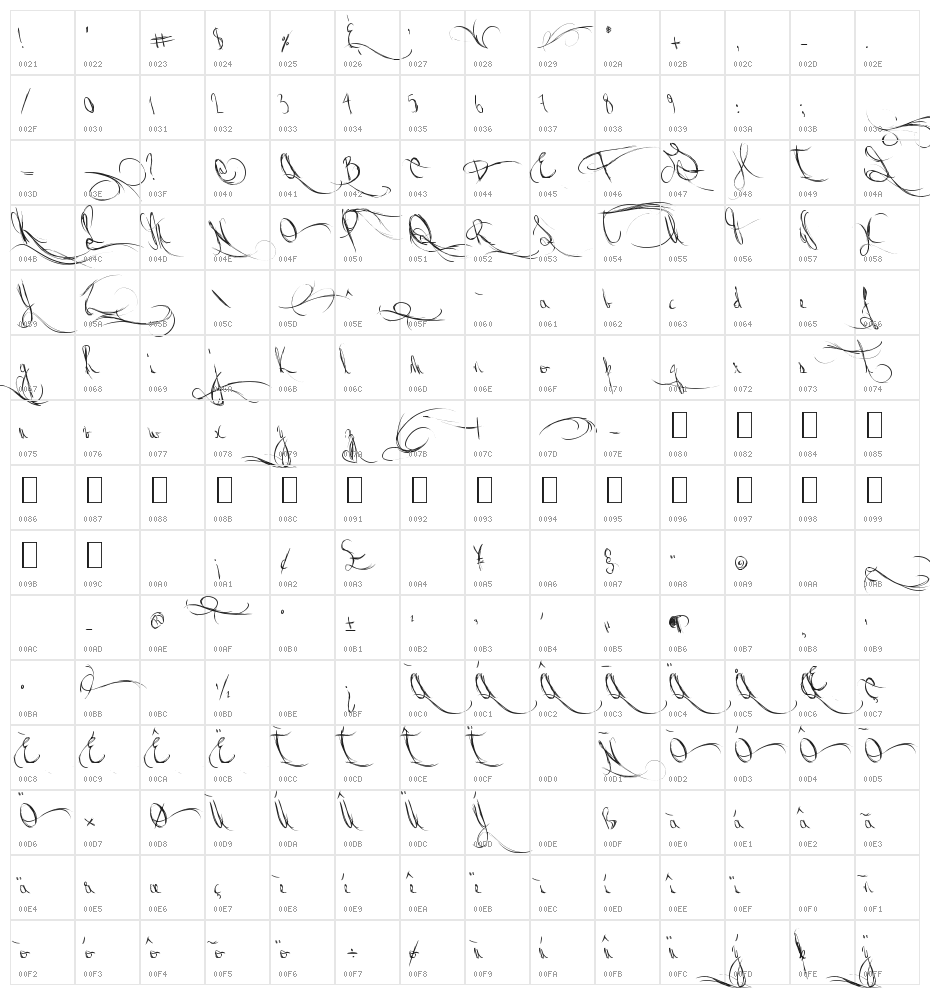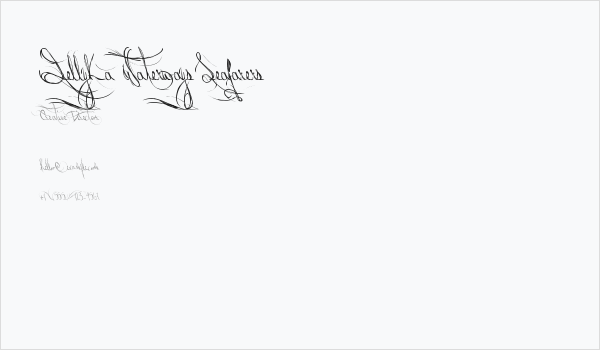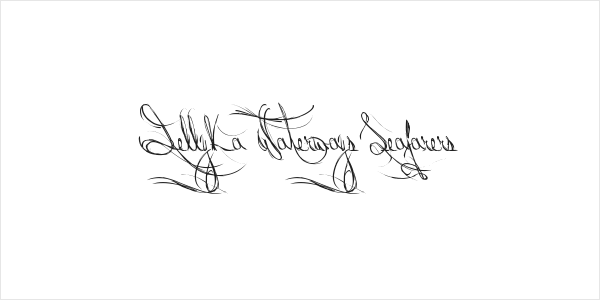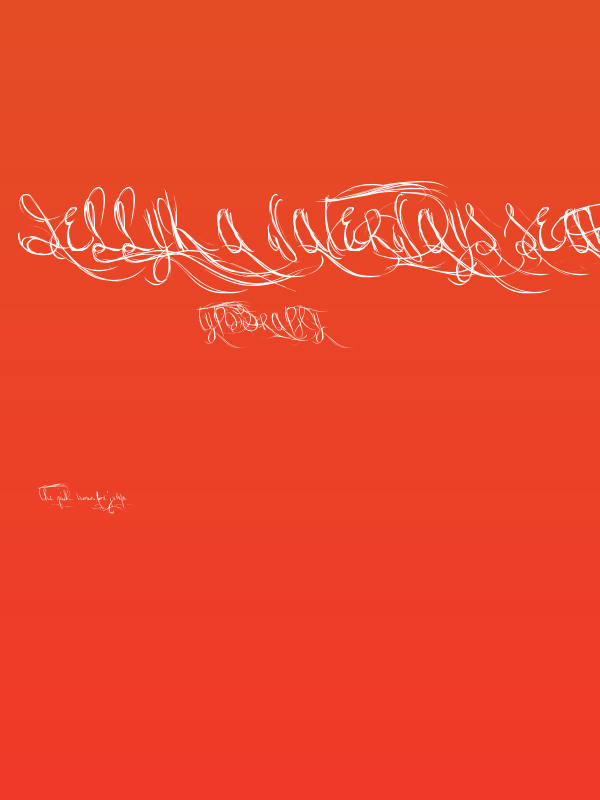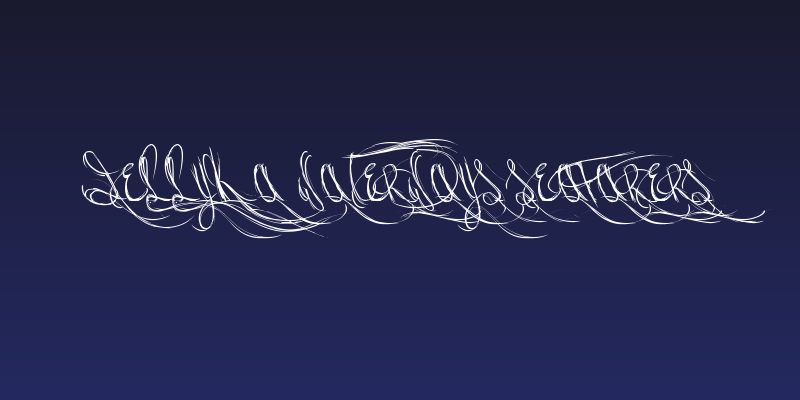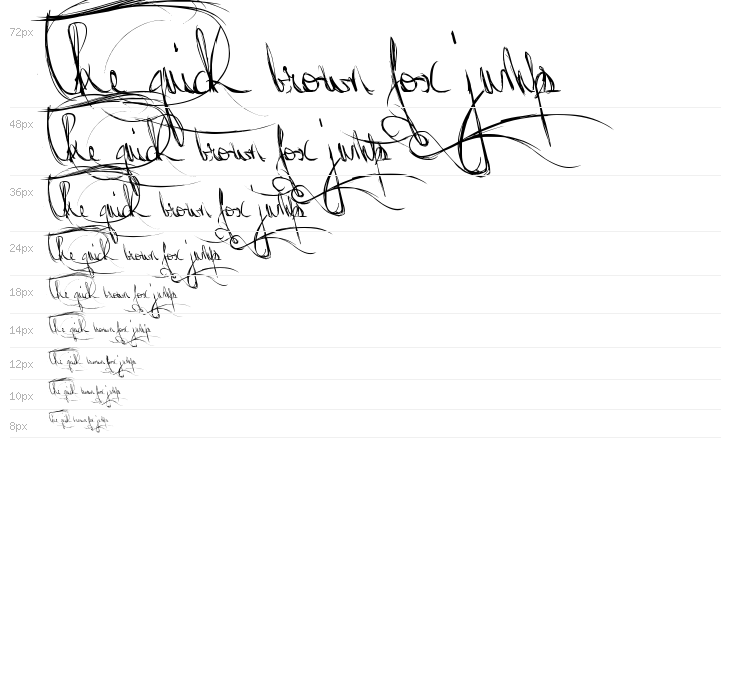
Jellyka Waterways Seafarers Font
✎ Calligraphic
| 分类 | Calligraphic |
| 斜体 | Yes |
| 使用场景 | Logos, Invitations, Artistic Projects |
| 推荐项目 | Ideal for wedding invitations, greeting cards, artistic posters, and branding materials that require a personal touch. |